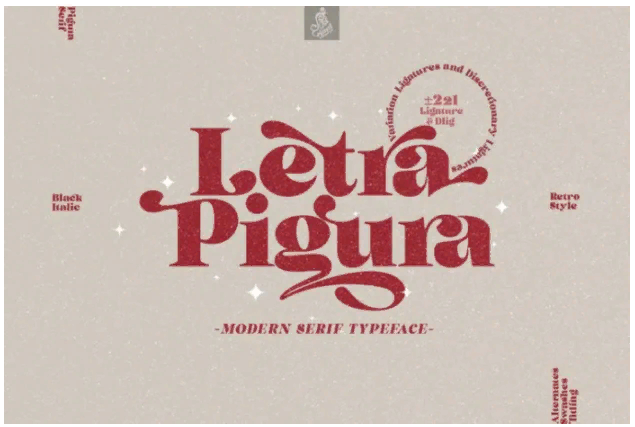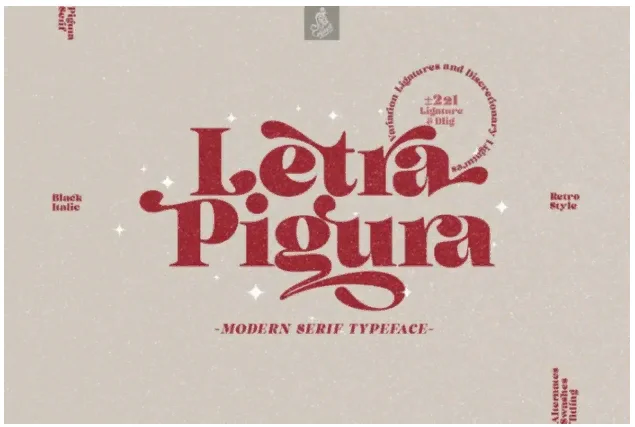
Название: Pigura Font (2021)
"Pigura Serif" - это шикарный, современный шрифт и элегантный ретро-шрифт с художественной ноткой винтажа, а также уникальным сочетанием лигатур на букве, так что авторы составили его с а и небольшими вихревыми вкраплениями, так что современный шрифт сформирован и готов сделать заявление, добавив элегантное и уникальное чутье к вашему следующему дизайнерскому проекту.
"Pigura Serif" может быть использован для различных целей, таких как заголовок журнала, плакат, логотип, футболка, подзаголовок, визитные карточки, журналы, обложки книг, свадебные приглашения, шаблоны Instagram Story Post, поздравительные открытки, цитаты и т.д.